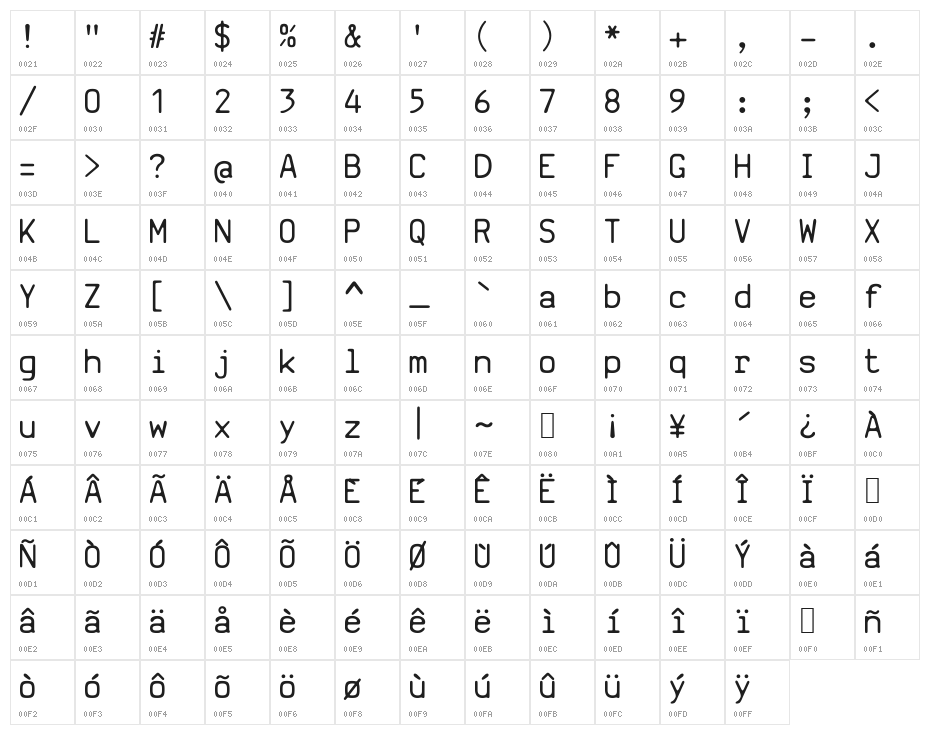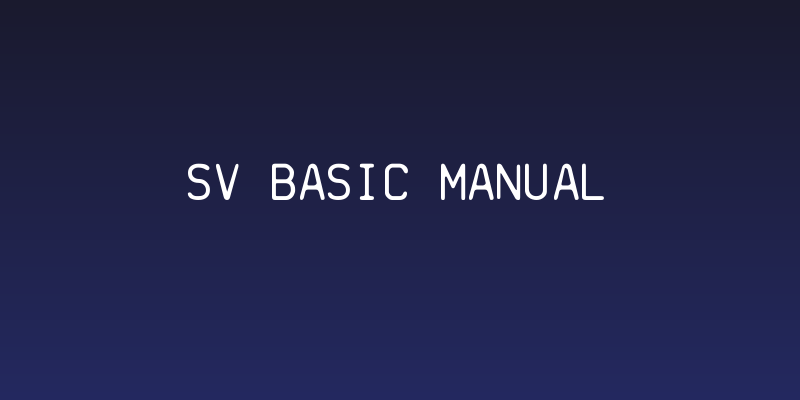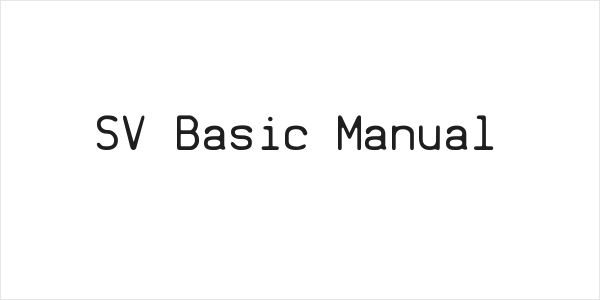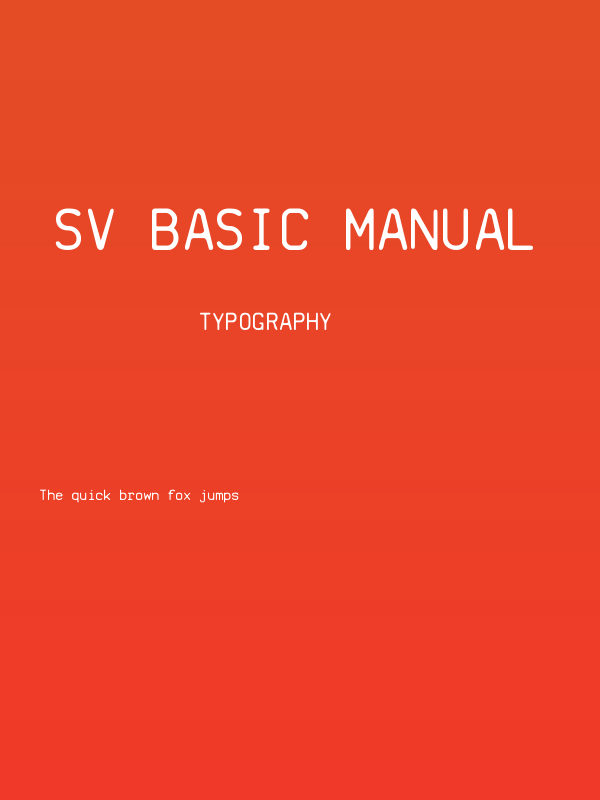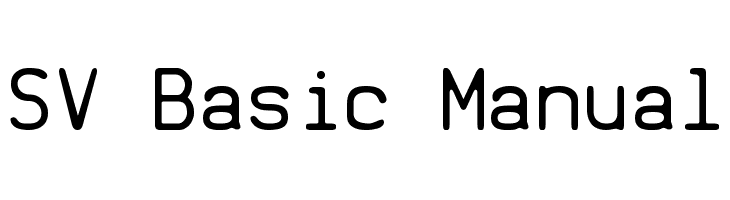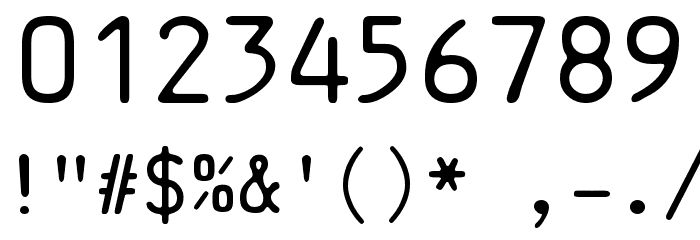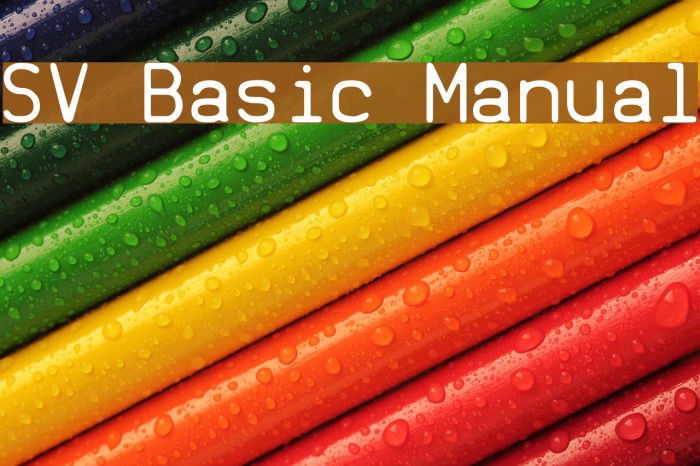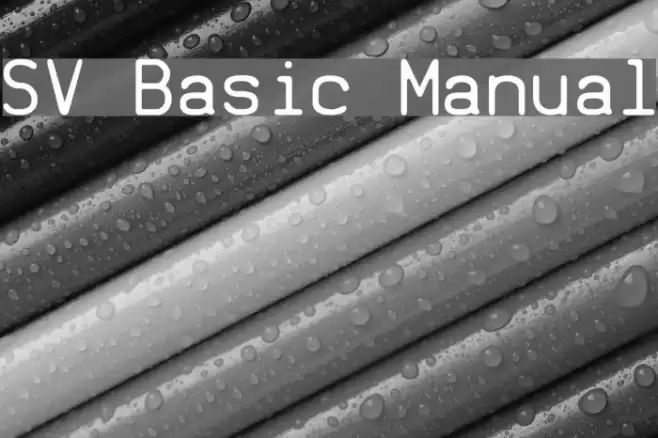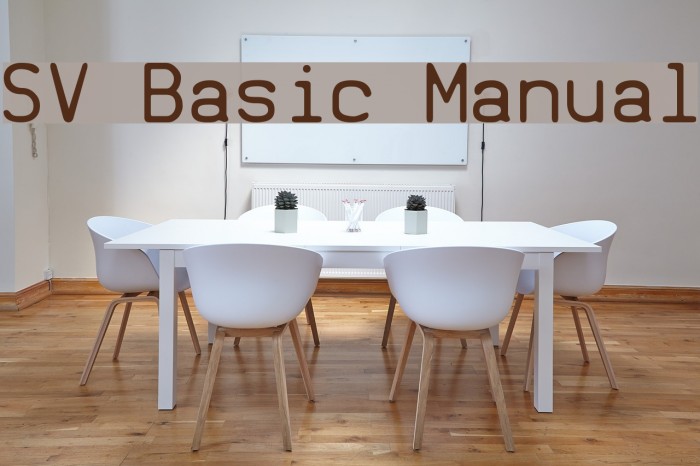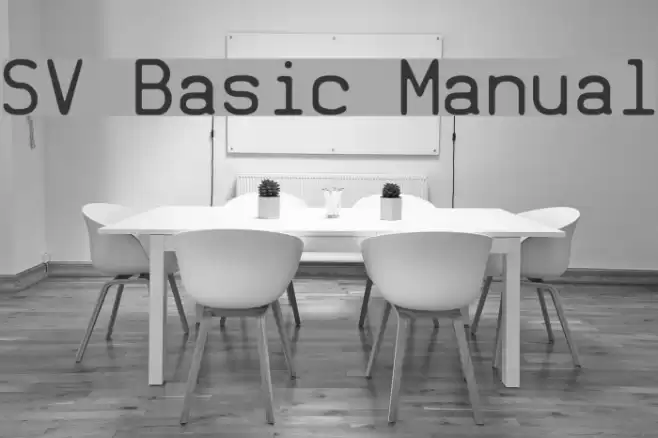
SV Basic Manual Font
| Progetti proposti | Ideal for user interfaces, educational materials, children's books, and branding projects that require a modern and approachable look. |